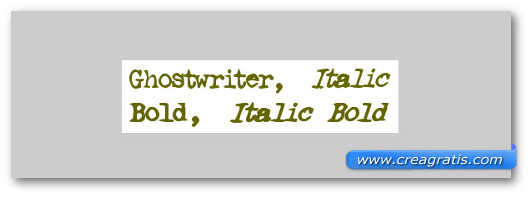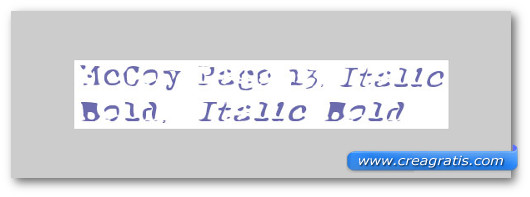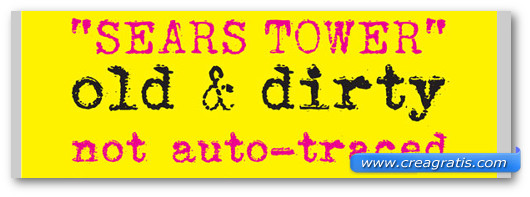
25 Font in Stile Macchina da Scrivere da Scaricare Gratis
Uso spesso il font Courier. Ma non per il suo apparire vintage, o per il suo richiamare una macchina da scrivere. No, mi piace perché ogni carattere ha la stessa larghezza, e quando stilo degli elenchi, oppure delle tabelle con numeri è comodo vedere subito la lunghezza delle parole, o i numeri con più cifre. Sopratutto quando tutti i numeri devono avere la stessa lunghezza, o quando le parole non possono essere troppo lunghe. Ammetto però che non è questo l’uso migliore da fare con i font in stile macchina da scrivere, anche con quelli da scaricare gratis. E sopratutto questi 25 che abbiamo raccolto in questo articolo. Sono tutti stilosi, ovvero pensati per dare un tocco di personalità a manifesti, volantini o pagine web.
Possono venire comodi per chi ha bisogno di un tocco grunge, magari per ricordare il western. Oppure per ricreare un’atmosfera d’inizio novecento, fine ottocento, quando scrittori e giornalisti usavano la macchina da scrivere, e i dispacci viaggiavano a cavallo. Quindi, lasciando perdere il romanticismo, ecco 25 font, più o meno artistici, in stile macchina da scrivere, tutti da scaricare gratis, tutti adatti per dare un tocco di stile, fascino e storia alle nostre creazioni.
1. My Underwood
2. Senta Schreibmaschine Font
3. USIS 1949 Font
4. Brenton Scrawl Type Font
5. Uncle Typewriter
6. Ghostwriter font
7. DK P.I. Font
8. McCoy Page 13 Font
9. Mechanical Fun Font
10. Rough Typewriter
11. Mom’s Typewriter Font
12. Old Typewriter Font
13. Teletype 1945-1985 Font
14. 1942 Report
15. Sears Tower Font
16. Typical Writer Font
17. F25 Blackletter
18. Old Newspaper Types Font
19. Metacopy
20. Typewriterhand Font
21. Cupid de Locke Font
22. Veteran Typewriter
23. Last Draft Font
24. Kosminen Taustasateily Font
25. DeLorimier Font